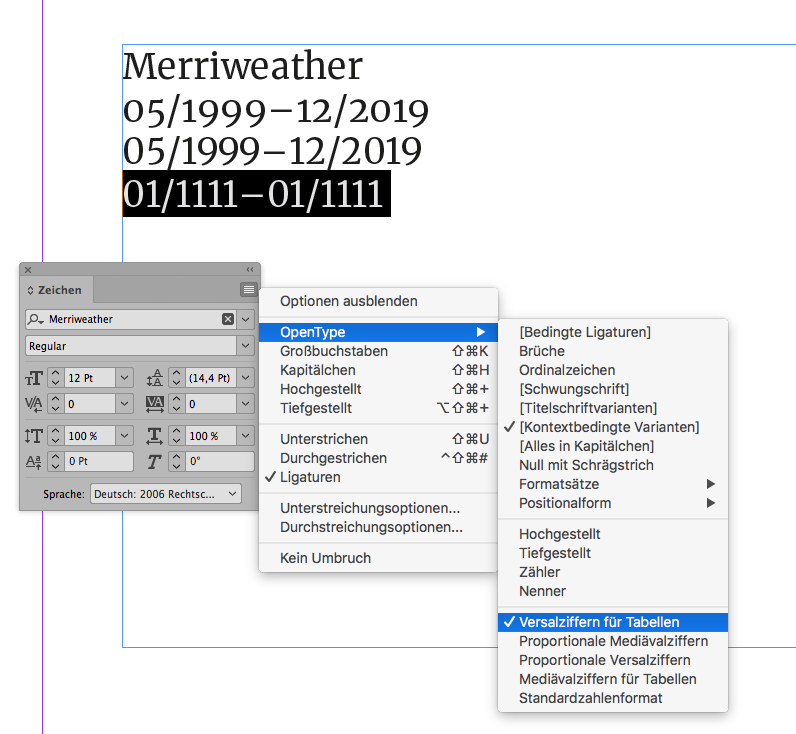
Indesign cc open type schrift mediävalziffern für tabellen
ich hab mir die open type schriftart merriweather von google fonts installiert
dort habe ich folgendes problem, für meinen lebenslauf habe ich die daten untereinanderstehen. jetzt habe ich mich schlau gemacht wie man in indesign das ganze ordentlich im tabellenformat formartiert.
und zwar über die open tyoe funktion mediävalziffern für tabellen oder versalziffern für tabellen. leider funktioniert das nicgt wie gewünscht, weiss jemand woran das liegen könnte?
hier ein beispiel von dem was ordentlich untereinander liegen sollte:
also die 11 unten im beispiel sollte genau den selben platz einnehmen wie die 05 darüber.
ich möchte ungerne über die laufweite einstellungen vornehmen, schliesslich handelt es sich um meine bewerbung und da möchte ich nicht stümpern.
Welche aber eben vom Font unterstützt werden muss. Das musst Du bei der Schriftwahl berücksichtigen. Die Version der Merriweather auf meinem Rechner hat diese Ziffern gar nicht im Repertoire.
Wenn es eine kostenfreie Font-Familie sein soll, die das können sollte, probier mal diese:
Ansonsten wäre die Meta Serif noch eine ähnliche aber kostenpflichtige Alternative:
achso, wo sieht man das denn? dachte da die in der open type funktion nicht eingeklammert sind stehen die zur verfügung...
danke für den tipp, werde ich mir mal ansehen, eigentlich suche ich folgende schriftart:
bin aber leider bei what the font nicht fündig geworden.
hast du vielleicht eine ahnung welche das sein könnte, bzw. welche ähnlich wäre?
Das ist eine Garamond. Davon gibt es zig verschiedene, wahrscheinlich hast du eh eine installiert ;-)
Zur Merriweather: Die Version auf FontSquirrel hat auch Versalziffern für Tabellen, allerdings funktionieren diese nicht, wie man sieht:
genau das ist das problem : )
woran erkennt man das eigentlich ob eine schrift das hat oder nicht?
Tja, das kommt etwas auf den Anbieter und Händler an. Da gibt es mehrere Optionen, zum Beispiel:
• Glyphentabelle
• Specimen-PDF
• Live-Vorschau, die Opentype Features unterstützt
Eine Live-Vorschau wie bei Myfonts.com ist aber aus meiner Sicht noch der verlässlichste Weg, da man darüber eben nicht nur sieht, ob die gewünschten Zeichen vorhanden sind, sondern auch, ob man diese wie gewünscht ansteuern kann. So etwas wird aber leider bisher nur von den wenigsten Vertriebsseiten angeboten.
hmm ganzschön verzwickt das ganze. naja, ich hab mal die garamond und die vollkorn ausprobiert, da funktioniert das wunderbar mit den Ziffern. Allerdings gefallen mir die Schriften nicht so gut. Ich hänge immer noch an der Merriweather. hab noch nichts gefunden was mir gefällt und wo auch die Ziffern in tabellen funktionieren.
Gibt es eventuell sonst sonst noch eine alternative die Ziffern händisch zu positionieren?
Mit der neuesten Version von GitHub sollte es funktionieren: